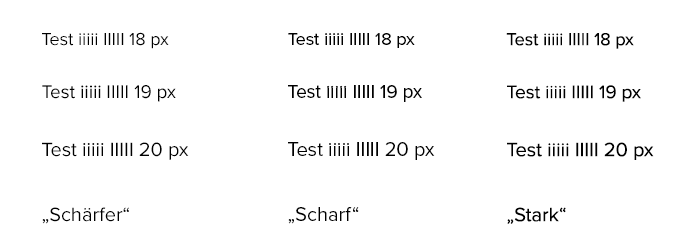
Welche Variante von Proxima Nova verwendet CNET.com?
ich rätsel über folgendem Problem: CNET verwendet Proxima Nova mit 17px. Manipuliere ich das CSS, so dass CNET mit 19PX angezeigt wird, kommt etwas das Bild im Anhang hier raus. Setze ich Proxima Nova auf meiner eigenen Website via Typekit ein, wirkt die Schrift deutlich fetter und bei exakt 19px gibt es einen Renderbug, bei dem die Details wie i-Punkte verschwinden und zu einer langgezogenen Linie fast wie ein l werden. Hatte jemand schon mal so ein Problem?
Ich hab’s mal ausprobiert:
Der Fehler bei 19 px ist reproduzierbar, Screenshot ist aus Photoshop.
… und mit verschiedenen Renderoptionen verschwindet der Fehler:
Nein, sagt mir leider gar nichts bzw. enthält es keine neue Information. :(
Irgendwas muss ja bei CNET anders sein, wenn sie bei 19px diesen Renderbug nicht haben? Bei 19.1 ist er weg...
Welche Optionen kämen denn überhaupt in Frage...kennt sich jemand mit diesem Open Type aus oder allgemein Font-Styling via CSS abseits der bekannten Optionen wie weight, style etc.
Webfonts sehen sowieso bei jedem anders aus. ;-)
Aber im Ernst: es kann am Unterschied zwischen PostScript- und TrueType-Outlines liegen, am gegebenenfalls vorhandenen/nicht vorhandenen oder anders definierten Hinting oder es einfach ein anderer Schnitt oder eine andere Version. Die Schrift ist ja schon ein paar Jahre alt und existiert in verschiedenen Varianten. Ein identischer Name alleine sagt noch nix.
Ich hab mal in den CNET-Font reingeschaut. Der ist Version 2.003 mit Copyright 2005 und 2015 wurde da scheinbar mit FontForge dranrumgeschraubt, was ein bisschen verdächtig ist.
Danke. Ausprobiert. Mein Setting ist offenbar Speed, bei
text-rendering: optimizeLegibility;
text-rendering: geometricPrecision;
verändert sich der Text, aber das i wird in beiden Fällen nicht gefixt. Bleibt immer ein durchgezogener Strich und die Schrift wirkt bei 19px deutlich dicker als bei CNET.
Gerade gesehen: Bei Buzzfeed.com genau das gleiche - nehmen auch Proxima Nova. Ich kann die Schrift ohne Fehler auf 19px setzen und sie sieht deutlich dünner aus als bei mir...seltsam ist das.
Kann mir jemand sagen ob das hier eine 300er oder 400er Fette ist?